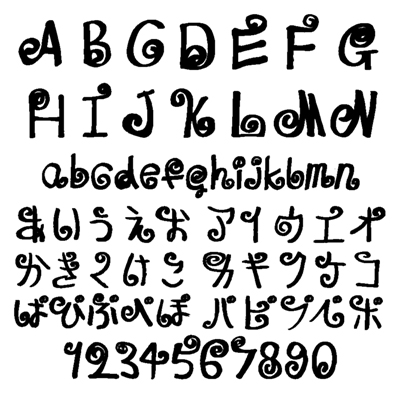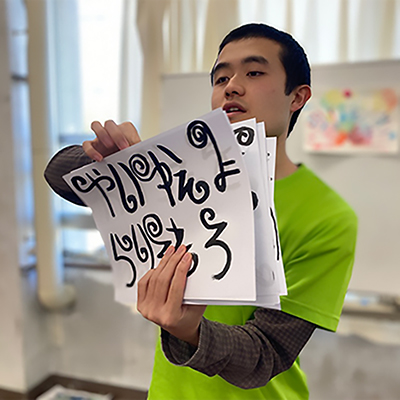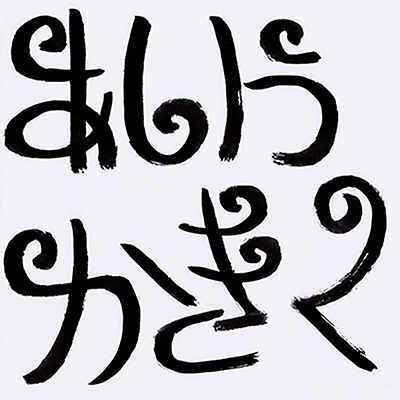
おさるのしっぽふぉんと
お猿のしっぽから生まれた、おさるのしっぽふぉんと!
天太は楽しんで作ってますので、楽しく使ってくれると嬉しいです(父)くるくるは、お猿のしっぽと、実はぞうの鼻もだよ。(河津天太)
くるくる文字のくるくるが、まさかお猿さんのしっぽとぞうさんのお鼻とは気がつきませんでした・・・(さとうひろゆき)
くるくるした文字は、おさるさんのしっぽとぞうさんの鼻だそうです。動物好きな天太さんから生まれたフォントを皆さんに使ってもらいたいです。(あそ美)